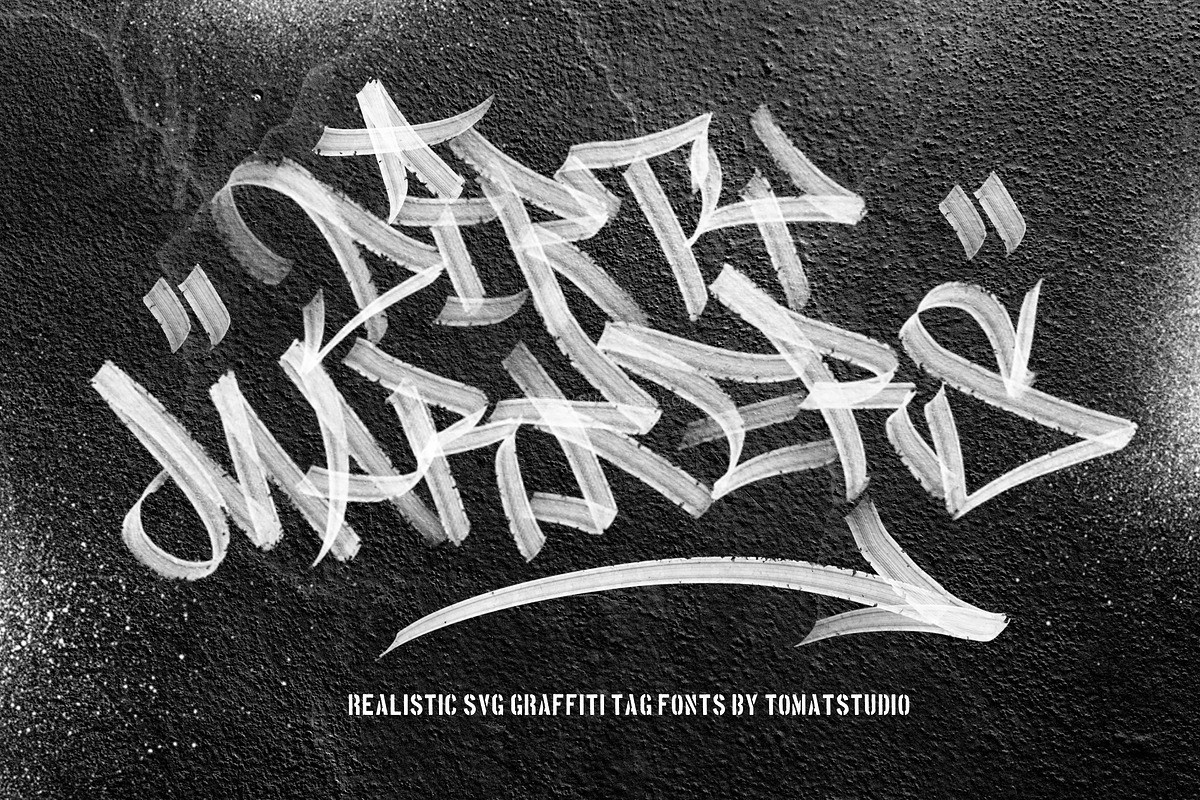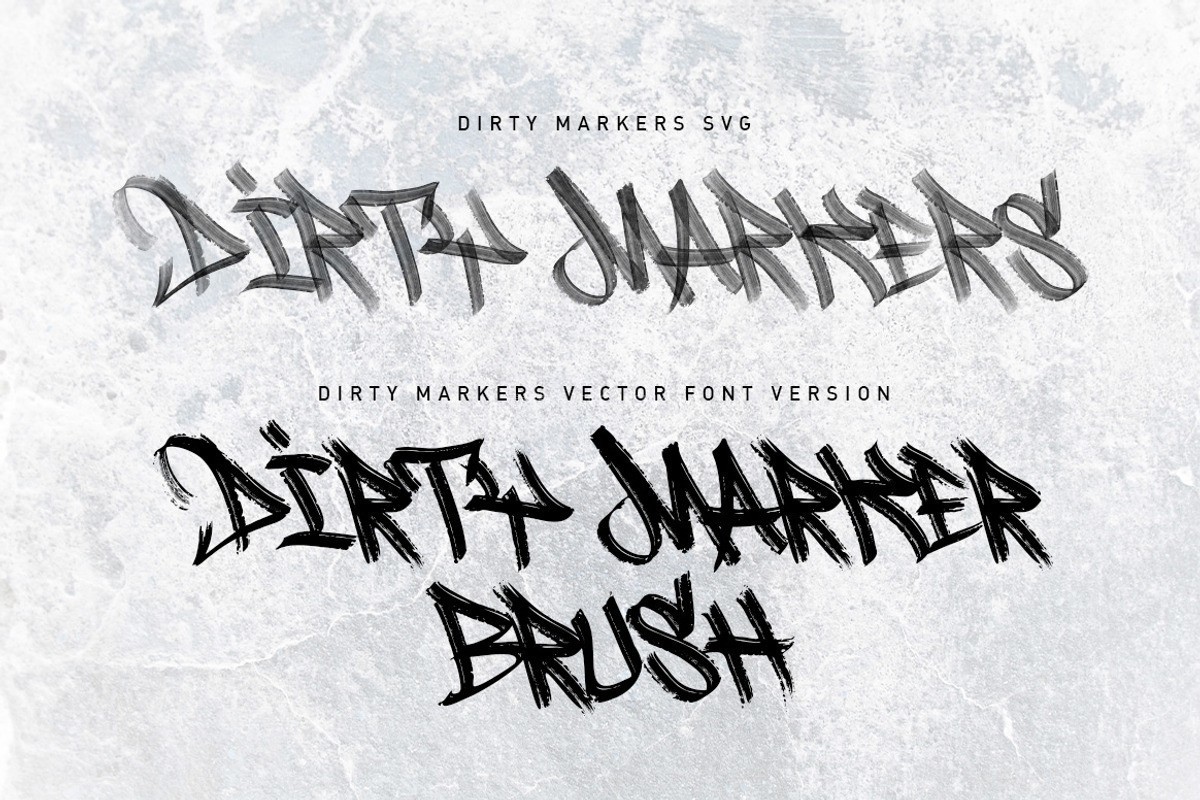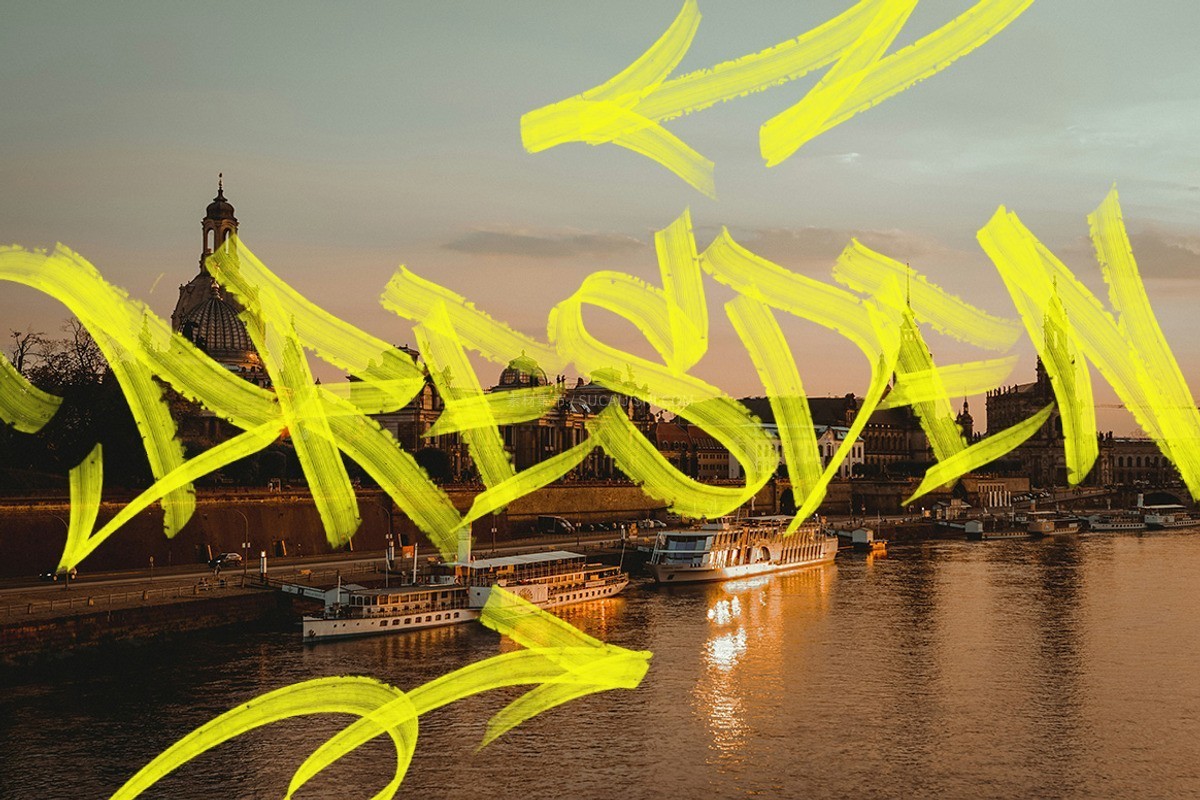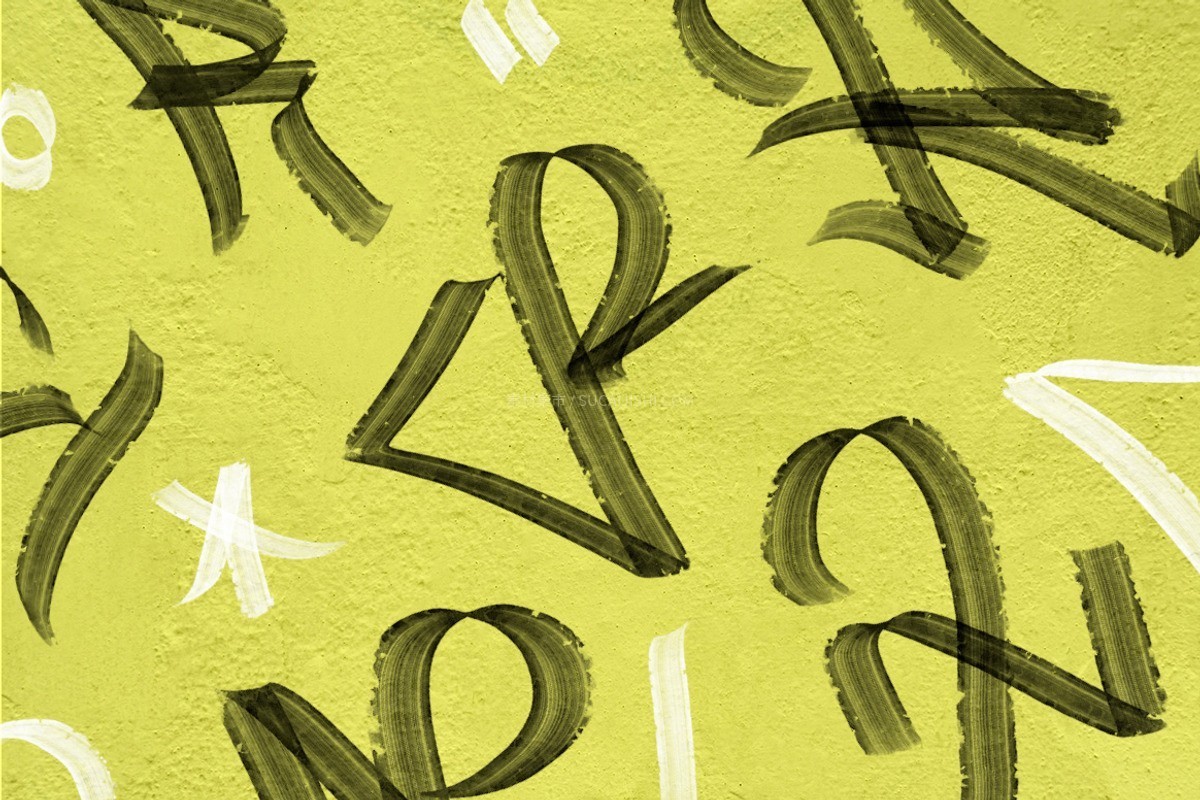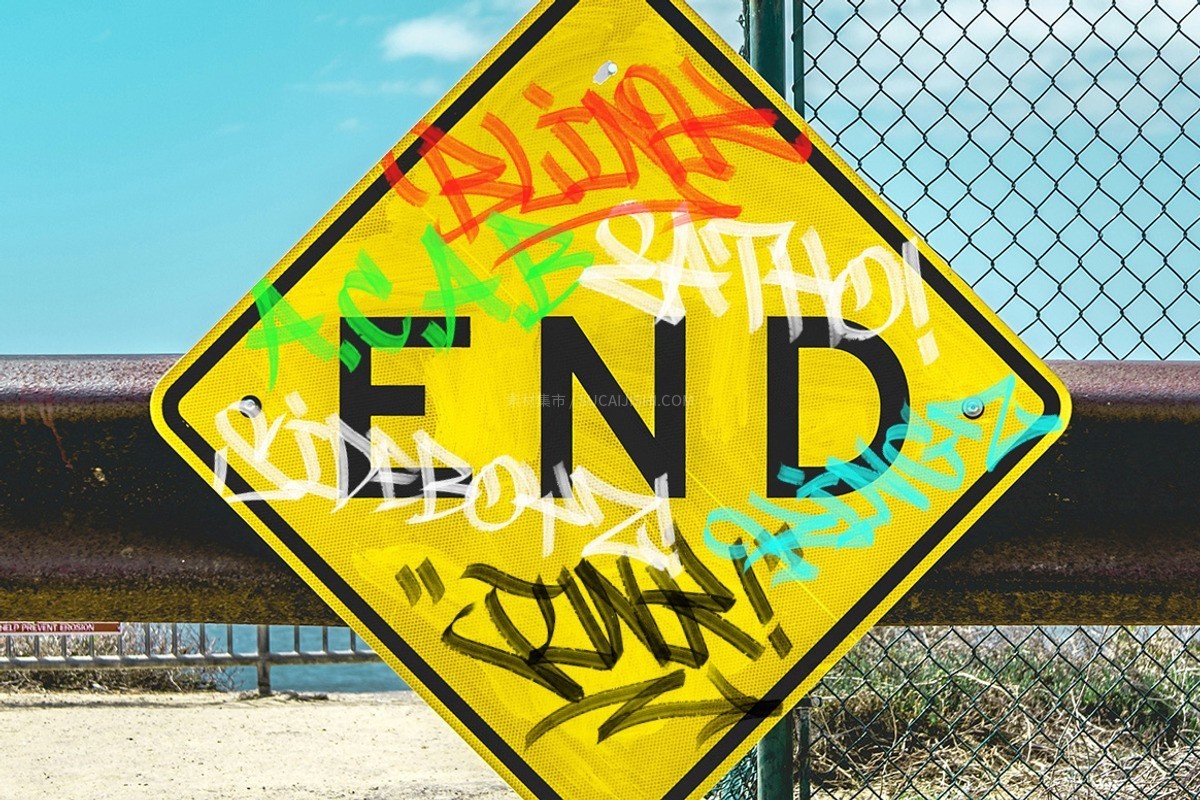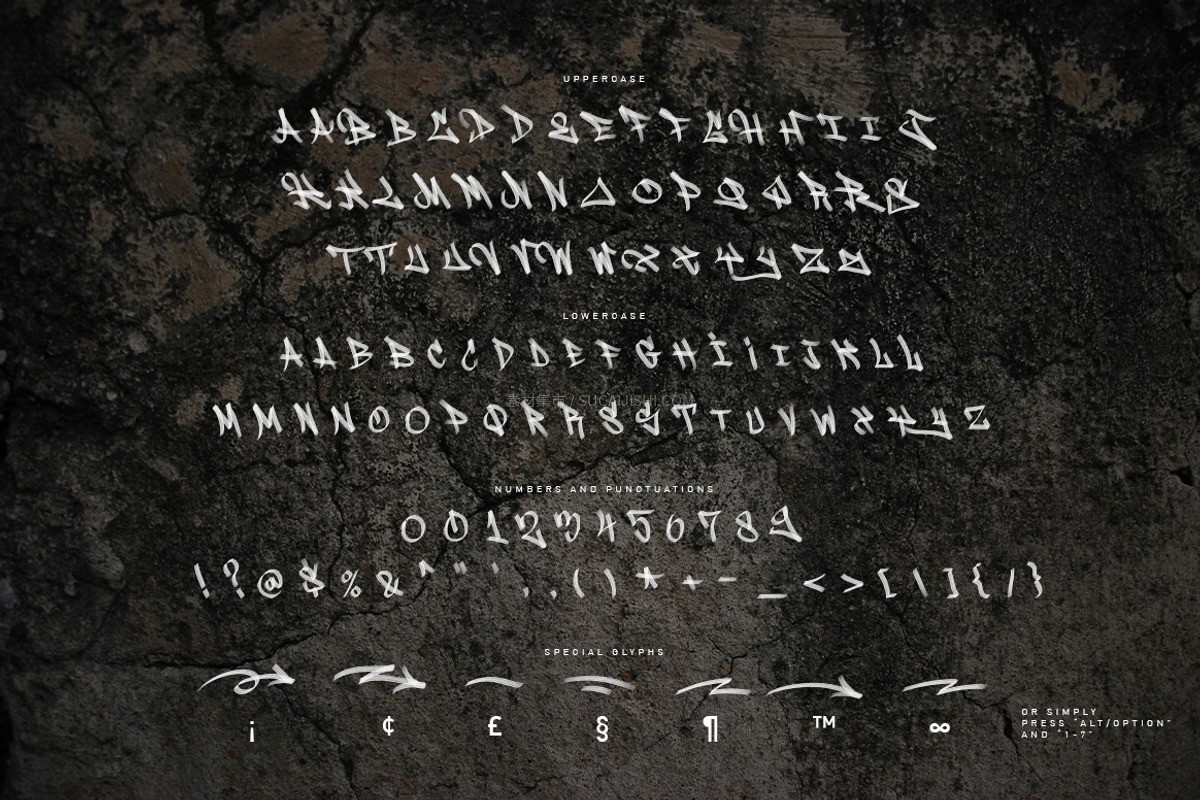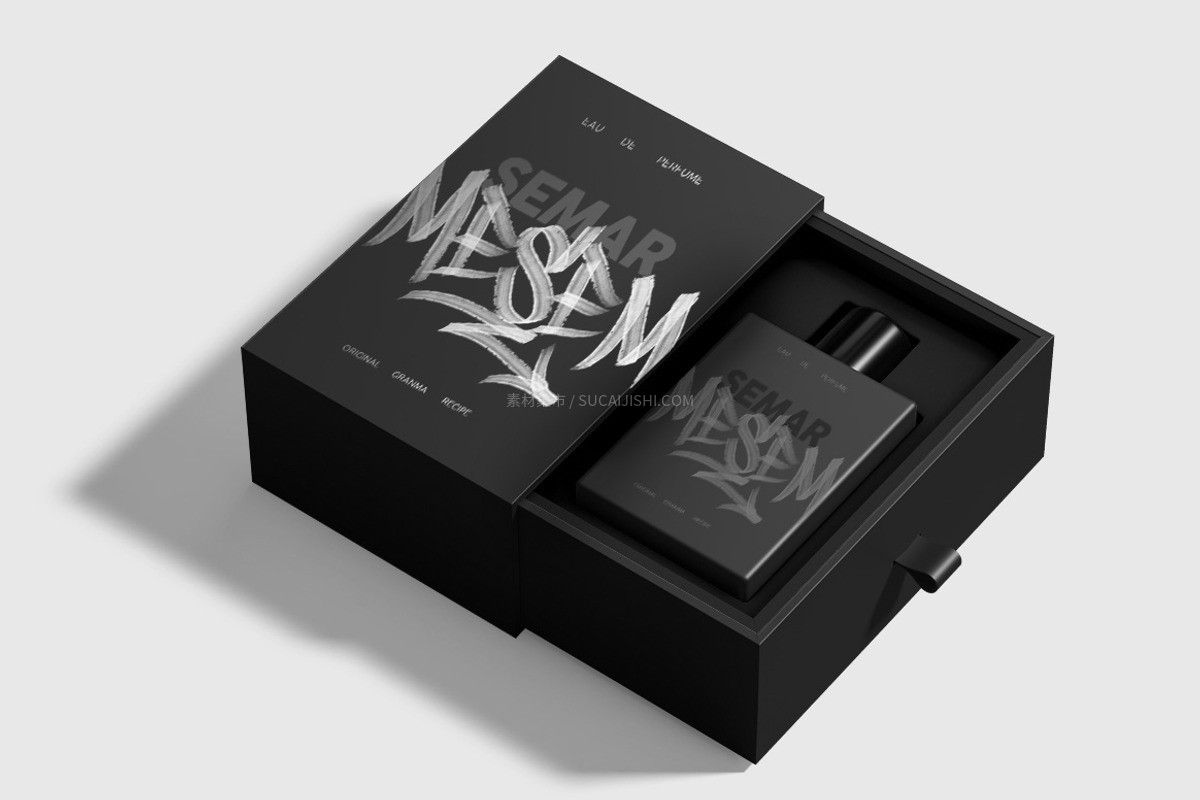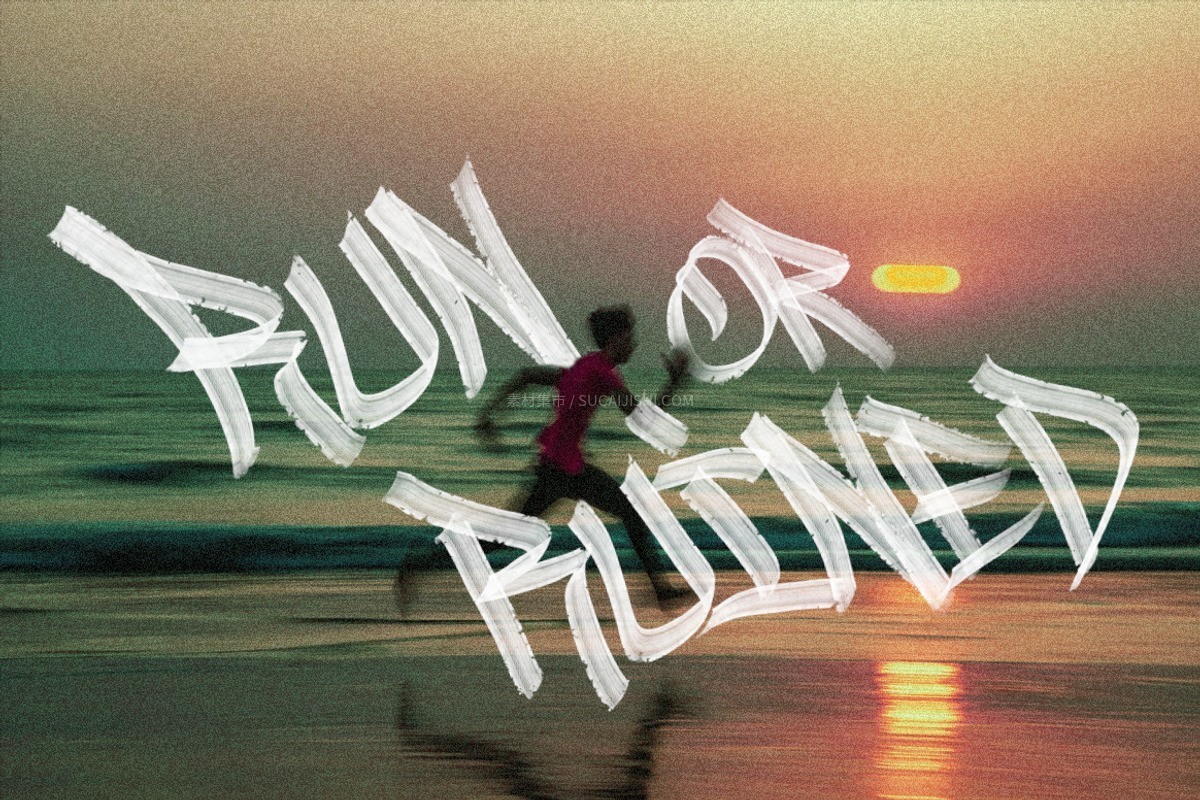
Dirty Markers 马克笔涂鸦SVG位图字体
这是一款由资深涂鸦艺术家亲手创作的专业级字体,完美还原了脏污马克笔(Dirty Marker)真实的物理质感与笔触。不同于普通的平面字体,它采用了 SVG 格式以保留精细的笔触细节与墨水干枯的边缘,让你的设计瞬间拥有纯正的街头艺术气息。
设计优化: 特别设计的大写字母适用于单词首字母,大写替代字母(Uppercase alternates)专为单词结尾打造,让整体排版更具节奏感。
特殊字符: 内置特殊符号(通过 alt/option + 1-7 快速呼出),为你的作品增加点睛之笔。